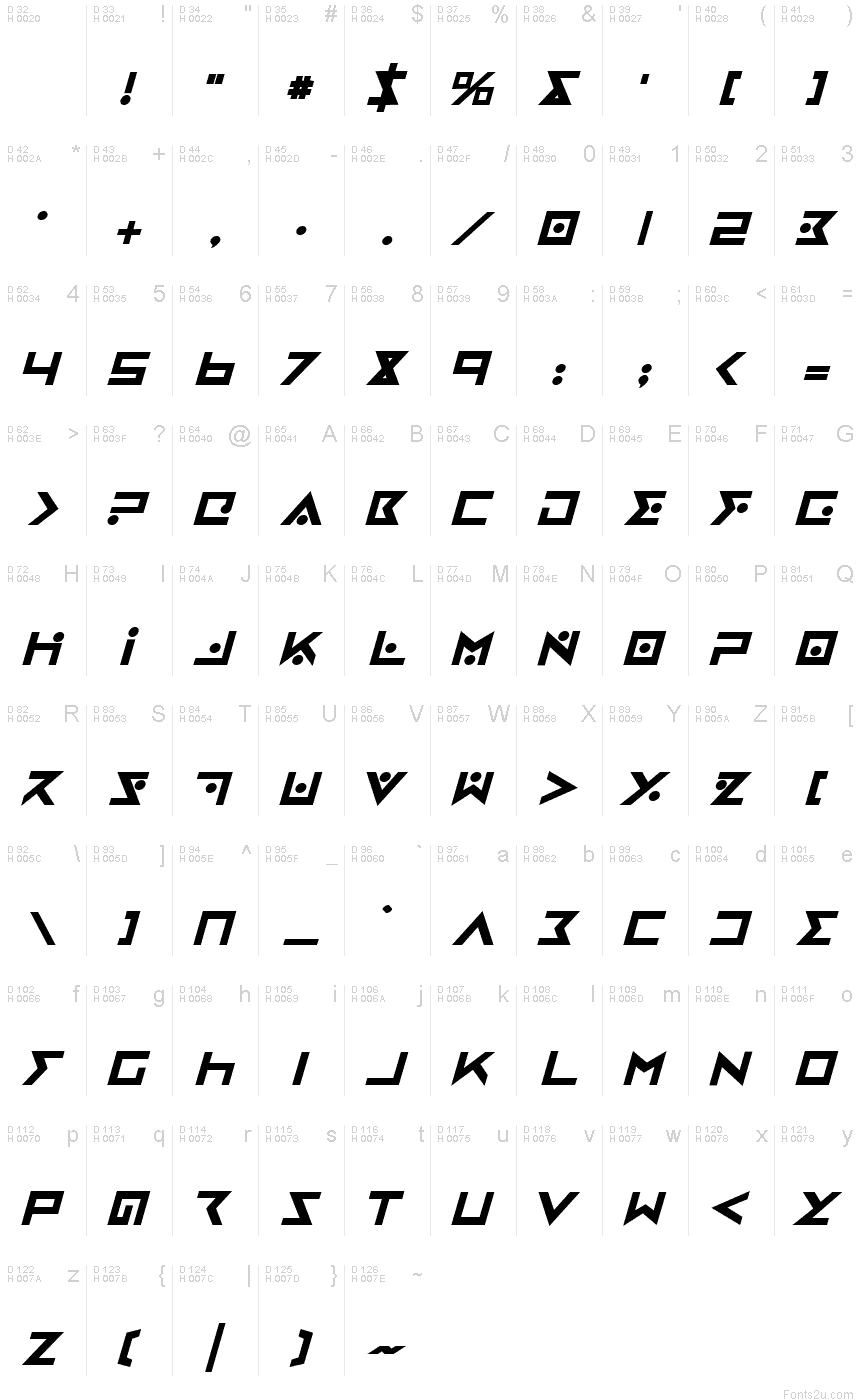
Iron Cobra od Iconian Fonts to darmowy, futurystyczny krój pisma typu display o wyrazistym, dynamicznym charakterze. Litery, pochylone do przodu, przypominają kształtem cięty metal – połączenie szerokich klinów i ostrych kątów sprawia, że font jest wręcz stworzony do logotypów science-fiction, brandingu technologicznego czy pełnych akcji nagłówków. Świetnie sprawdza się na opakowaniach gier, plakatach, grafikach streamingowych, materiałach esportowych i planszach tytułowych, gdzie potrzebny jest efekt ruchu bez utraty czytelności. Dzięki ostrym, kierunkowym formom, sprawdzi się również w krótkich logotypach, nazwach frakcji czy oznaczeniach interfejsu, które wymagają napiętego, mechanicznego wyrazu.
Iron Cobra Bold Italic